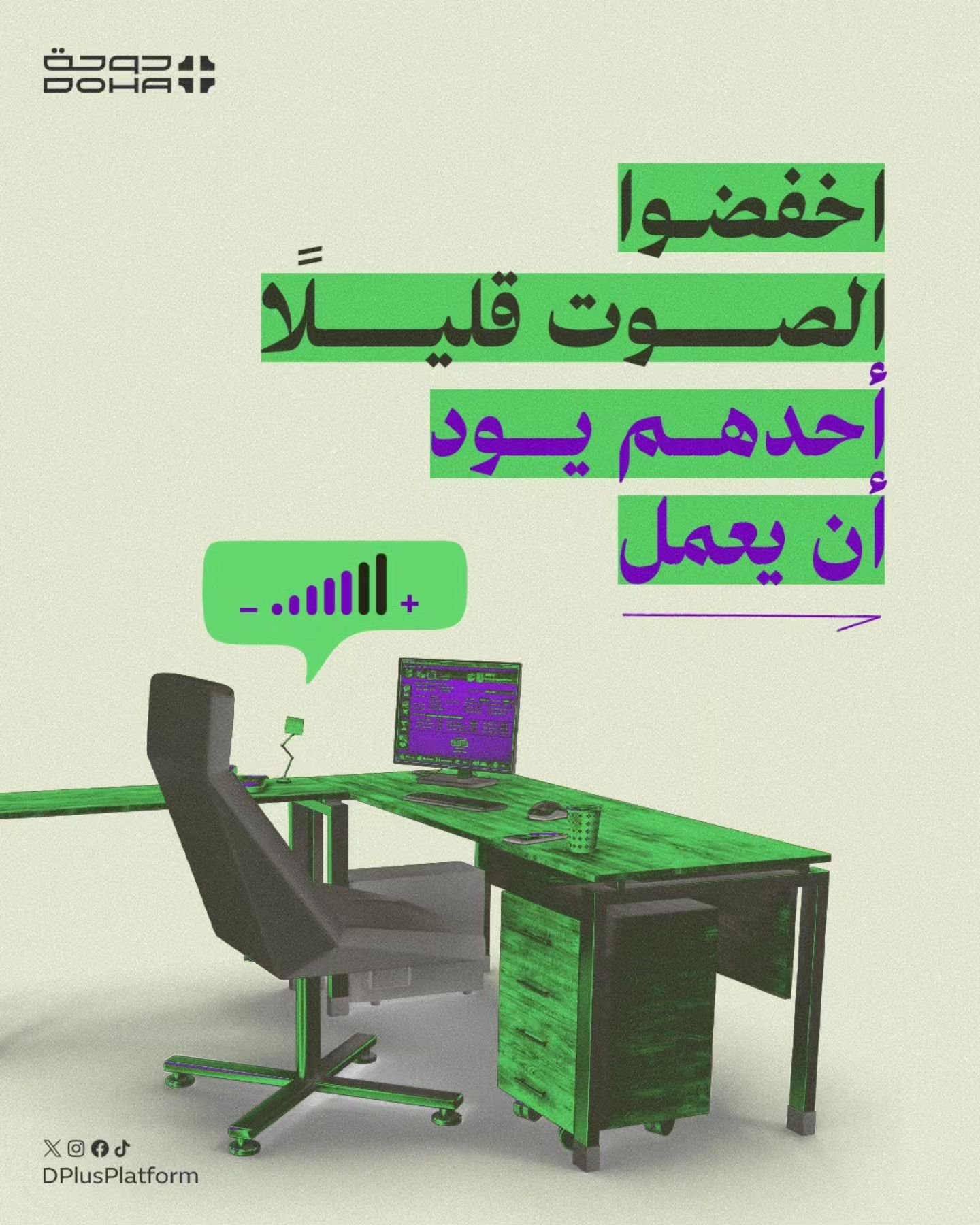
استخدام خط فاطمة عربي – Doha Plus
فاطمة عربي هو خط طباعي عربي حديث يستلهم من أسلوب الخط النسخ، ويتميز بتباينه العالي ونسبه المتقنة.
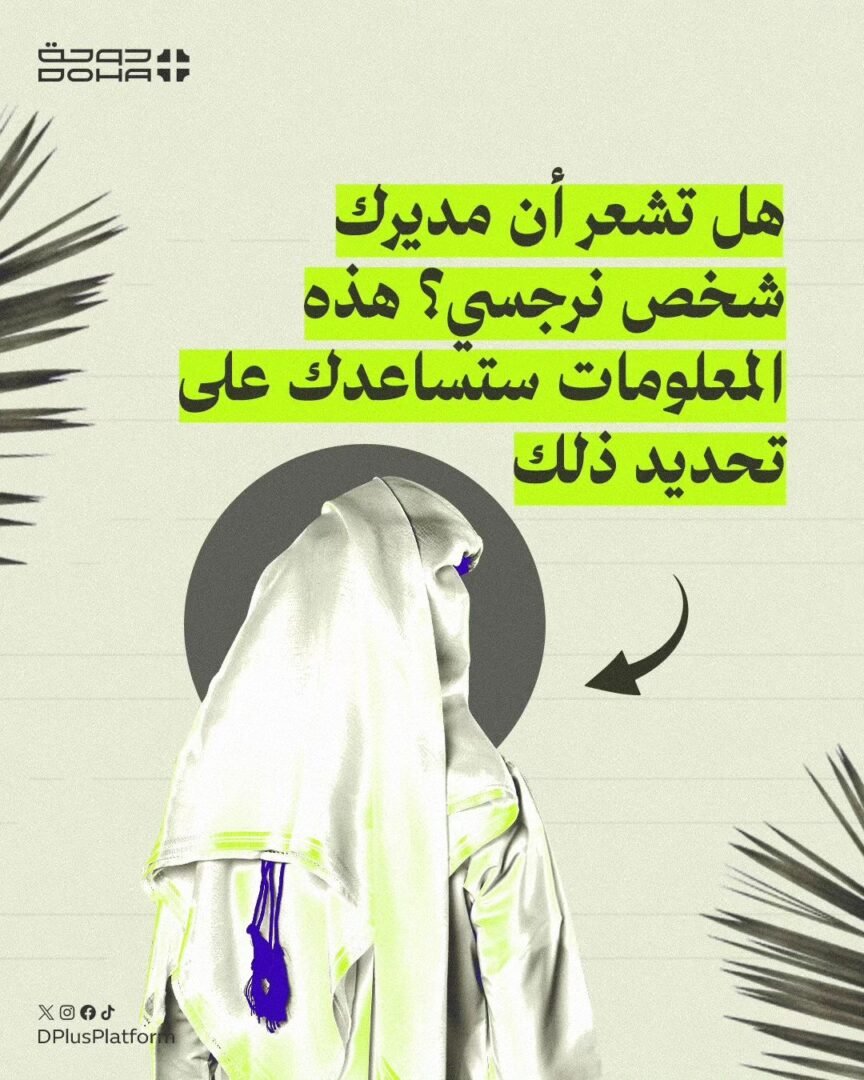
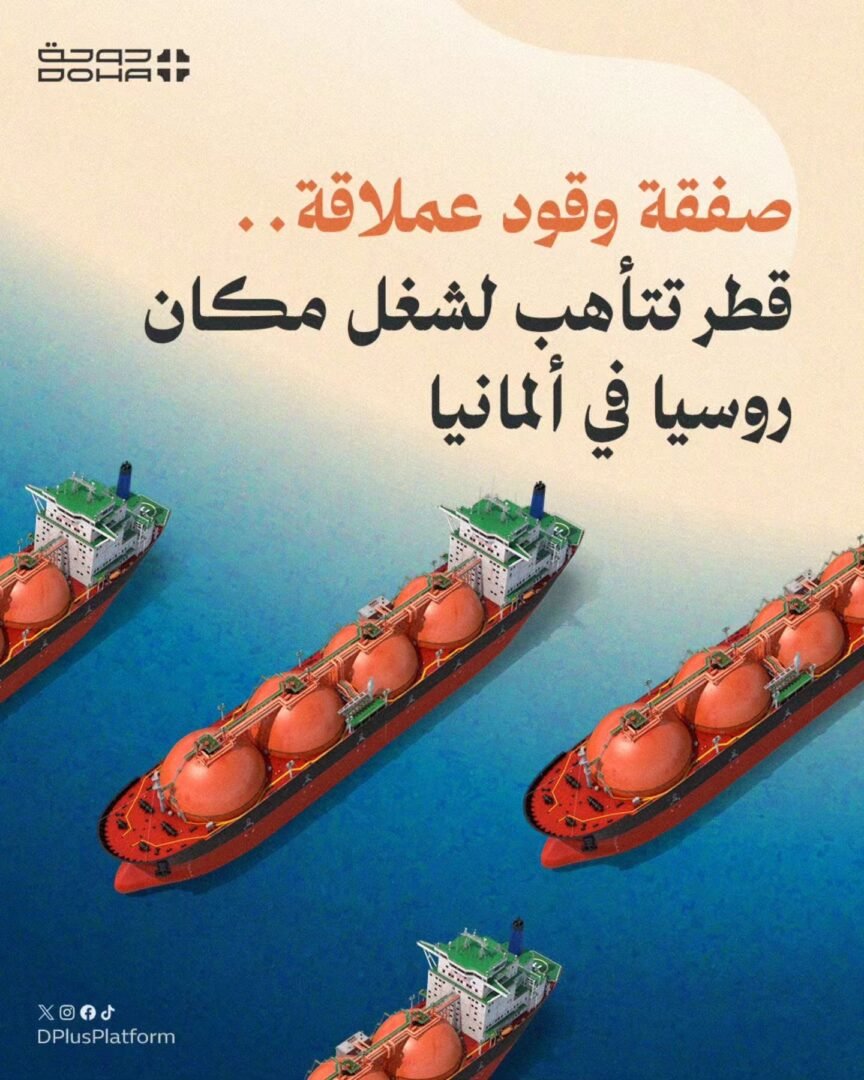
فاطمة عربي هو خط طباعي عربي حديث يستلهم من أسلوب الخط النسخ، ويتميز بتباينه العالي ونسبه المتقنة.